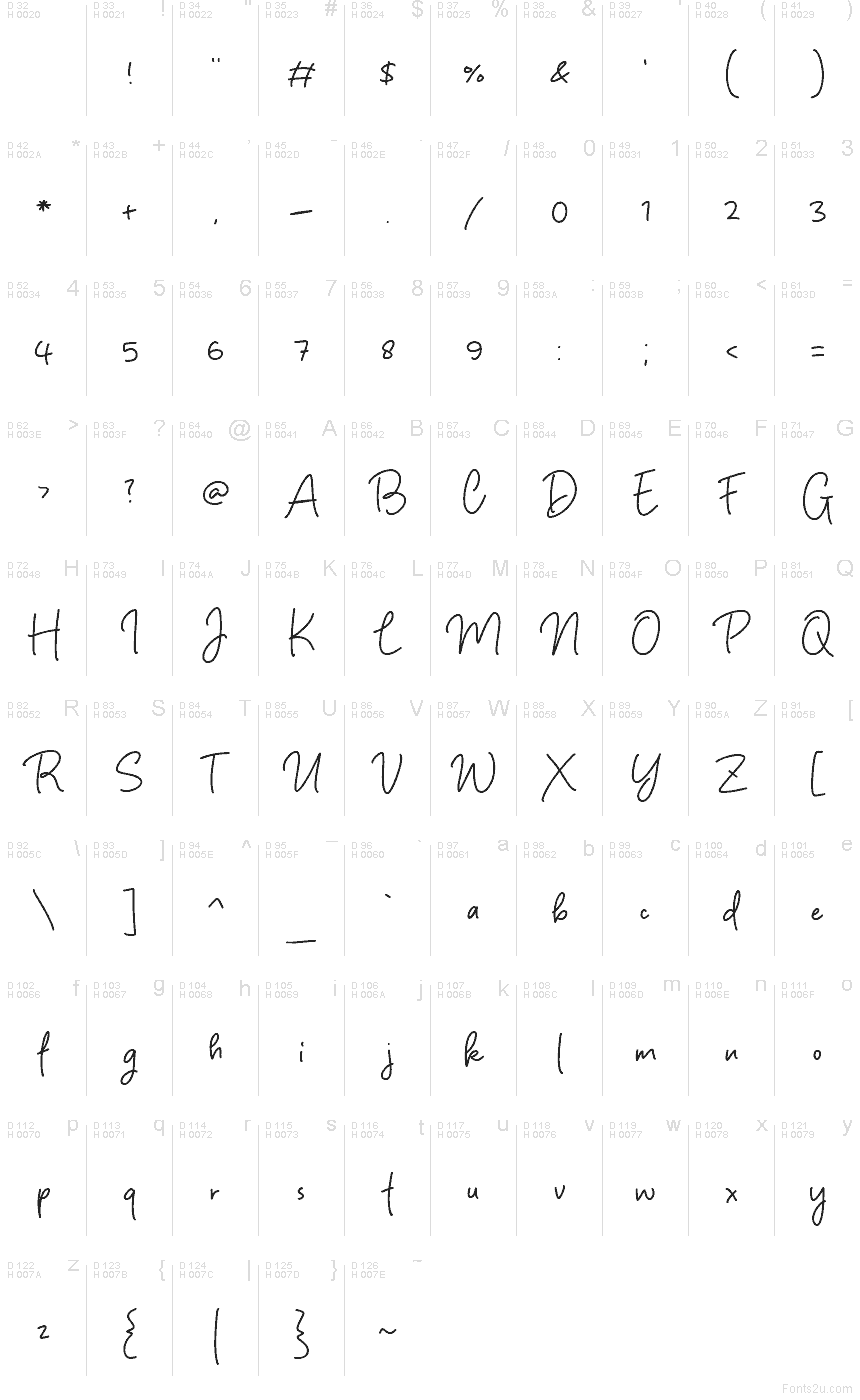
Bloom Velvet od MJType je bezplatné ručně psané písmo s uvolněným charakterem připomínajícím tahy perem a se zaoblenými, propojenými znaky. Jeho tvary si zachovávají přirozený rytmus a vysoká počáteční velká písmena spolu s jemnými smyčkami dodávají celému písmu uvolněný, osobitý nádech.
Bloom Velvet skvěle funguje na pozvánkách, v logotypech, grafikách s citáty, na etiketách obalů nebo v záhlavích na sociálních sítích, kde je žádoucí styl ručního podpisu. Toto bezplatné písmo přináší dostatečnou plynulost pro krátké nadpisy, přičemž si zachovává jednoduchost a známý vzhled, takže skvěle zapadne do brandingu, tiskovin, produktových štítků i grafiky na blogy, aniž by působilo zbytečně složitě.